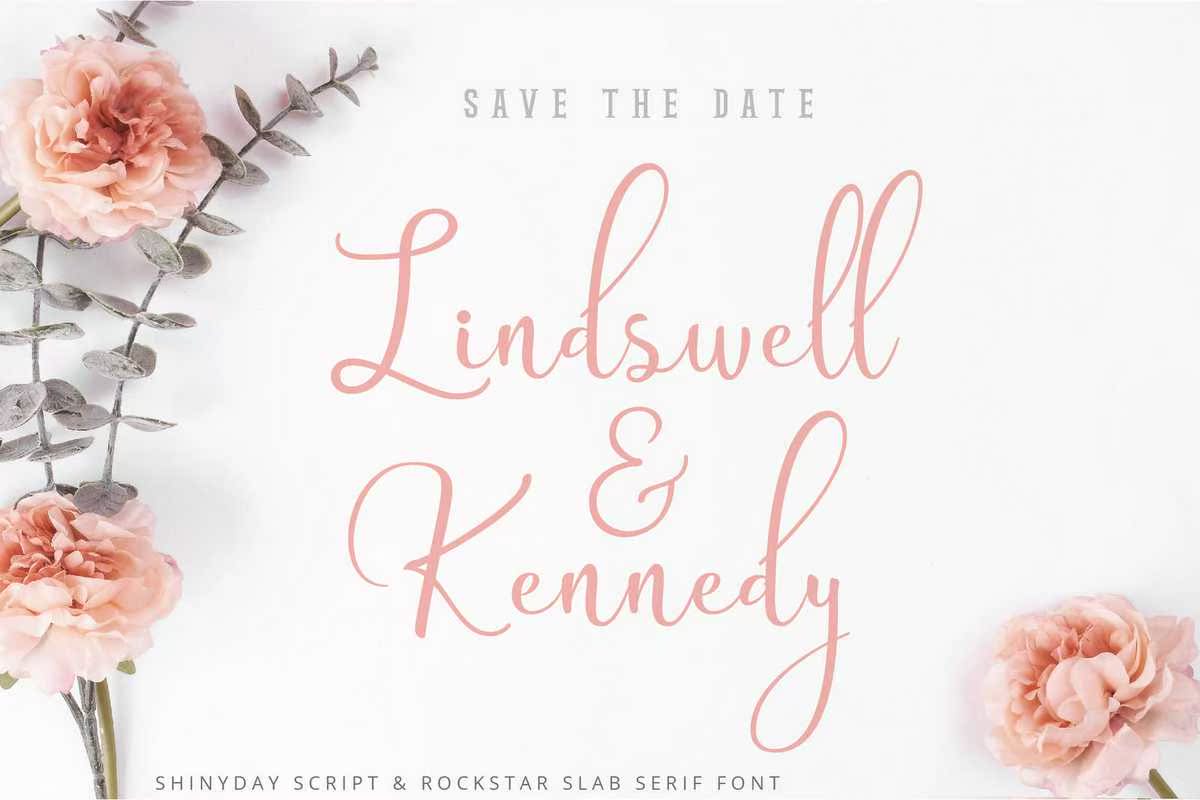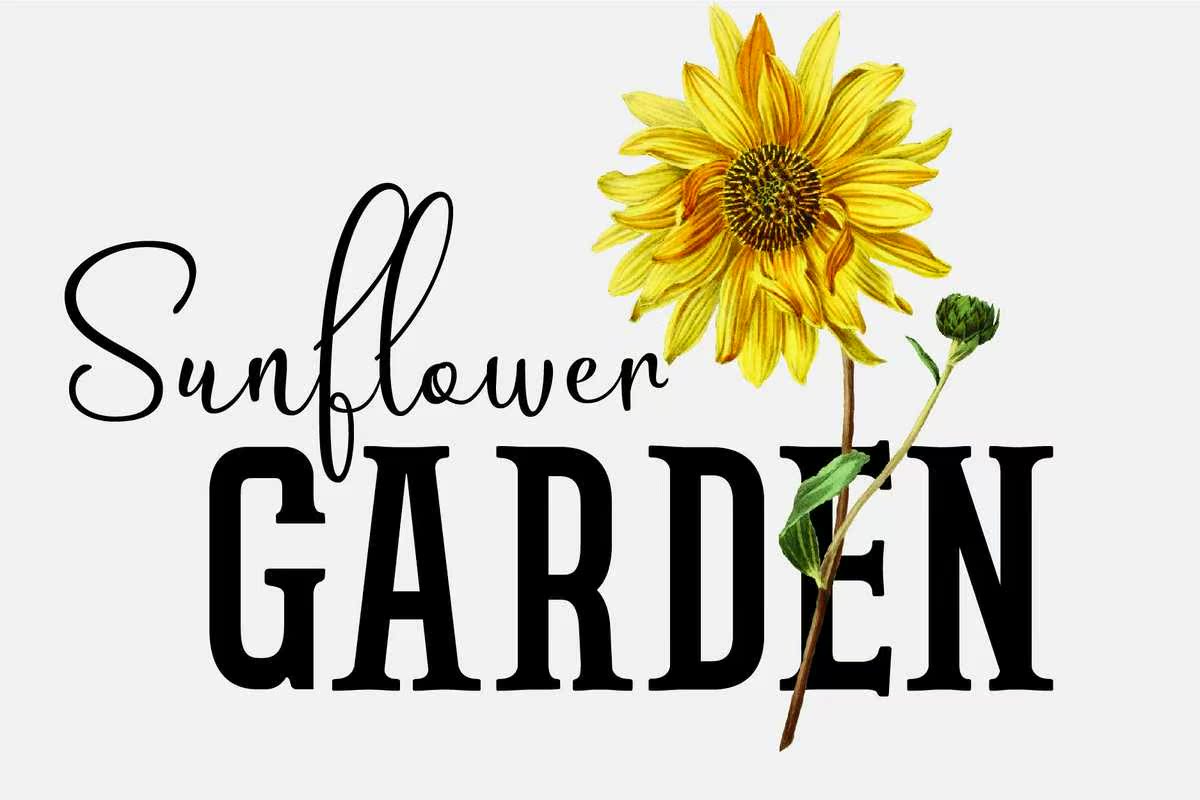
Shinyday是一种时尚而传统的脚本字体,有一些甜美的风格可供选择。它是一种女性化的字体,但同时也是一种高质量的字体,与摇滚明星(ROCKSTAR)结合在一起,是一种密集的斯拉夫风格。像我一样,这种字体强烈而富有精神。这种双重组合包括了戏剧、展示、海报、博客、女孩和女性主题、社交媒体,品牌和更多。Shinyday是时尚和传统的脚本字体,有一些甜美的风格可供选择。它有女性化的网络风格,但也有高质量,与摇滚明星(ROCKSTAR)相结合,这是一种密集的斯拉夫风格。像斯内姆一样,这种字体强烈而有精神。这是一种双重组合,包括小品、展示、海报、博客、女孩和女性主题、社交媒体、品牌等等。